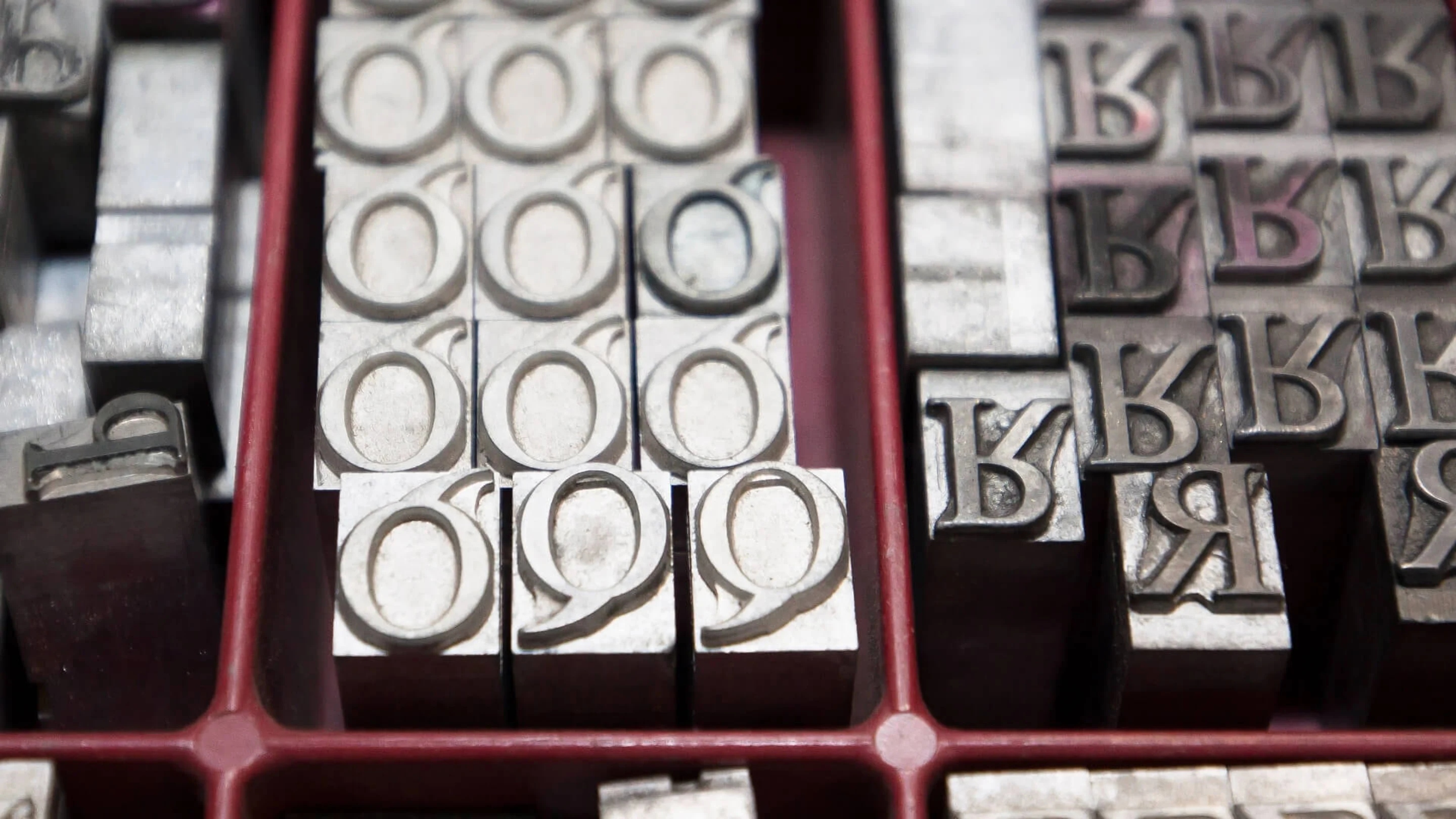
ご存知のとおり、サンセリフ書体はPCでの作業やオンライン上のテキストを表示する際に幅広く使用されています。その一方でセリフ書体は、昔から変わることなく紙媒体のデザインに適しています。
セリフ書体を認識するのは非常に簡単。それぞれの文字のストローク(一筆の動きのこと。aやeであればストロークは1つ。fやtであればストロークは2になる)の端にごく小さな線(例えば、ボール・ターミナル:文字の端に施される球状の装飾のこと、もしくはセリフ:ストロークの端にある飾りのこと)があるのがセリフ書体です。読みやすい文字という事実と離れた視点からみても、セリフ書体は、読み手に負担をかけることなくスムーズに次の文字を目で追うことができ、また認識しやすくしているのです。
昔から使用されている伝統的なタッチをあなたのデザインに取り入れられるよう、素敵なフリーのセリフ書体を厳選してみました。
まずご紹介するフォントは、Fabian De Smetがデザインを手がけた「Butler」です。 BodaniとDala Flodaのフォントからインスピレーションを得て作り出されたこのフォントは、本・ポスター・見出しや招待状でつかうとピッタリです。
Cyril Mikhailovがデザインを手がけた「Fakedes」は、丸みを帯びた2つの線から成るセリフ書体です。見出しでの使用がこの上なく似合います。
Classic Romanフォントからインスピレーションを得た「Forum」は、主にタイトルや見出しで使用するためにデザインされました。それだけではなく、パラグラフ(上記画像のような、ひとまとまりの文章のこと)での使用も素敵ですね。Denis Masharovがデザインを手がけたフォントです。
「Muchacho」は、独特な雰囲気のある全て大文字のフォントです。 Jeff Schreiberがデザインを手がけたこのフォントは、見出しで使うのにふさわしいでしょう。
Nicolás Silvaがデザインを手がけた「Poly」は、縦線を強調し、グリフ(文字の骨格作る抽象的な考えのこと)のあるウェブフォントです。
Iván Núñezがデザインを手がけた「Barbaro」は、1960年代の雰囲気を漂わせたいデザインにピッタリなヴィンテージ感のあふれるフォントです。
SuperBruutが作成した「Le Super Serif」は、88本もの合字(隣り合う文字を接続する手法のこと)と特殊な代替文字を使用した、見るからに流行を意識したフォントです。
Sean Coadyがデザインを手がけた「Firefly」は、手書きのような独特ののセリフ書体です。ヴィンテージ風な雰囲気を瞬時に見る人に伝えてくれますね。
Bodoniフォントからインスピレーションを得てデザインされた「Pelmeshka」は、ブログの見出しから子ども用の本まで幅広い用途にピッタリ。Cyril Mikhailovがデザインをした、見ていて楽しくなるようなフォントです。
Fernando DíazとTipoType Foundryによりデザインされた「Fénix」は、非常に強いインパクトのあるセリフと力強さを感じるストロークにより構成されているため、おしゃれな見た目になっています。見出しとパラグラフのどちらに用いても読みやすいこと間違いなしです。
ヴィンテージ風のフォント「Akura Popo」は、Twicolabs Designにより作り出されました。力強さのある見た目とクラシックな雰囲気を凝縮したようなセリフ書体です。
Pedro Loboがデザインを手がけた「Molesk」は、見た目のとおり、古い書体からインスピレーションを得たスラブセリフ書体(スラブセリフ:読みやすさを保ちつつ、太さを強調したセリフ書体のこと)です。素晴らしい見栄えの文字に少し注視してみましょう。それぞれの文字にレンダリングされた影がうっすらと浮かんでいますよね。このちょっとした工夫が、文字の仕上がりにより素晴らしいエッセンスを加えているのです。
「Rancho」には3つのスタイルがあり、全てのスタイルにワイルドウエスト(アメリカの西部開拓時代:1860年代~1890年頃)の雰囲気があります。さまざまな用途に使用できるこのフォントのデザインは、Nach Oh!によるものです。
この美しい「Bariol Serif」のデザインを手がけたのはAtipo。「Bariol Serif」は、スッキリとした線で構成されていて非常に読みやすいフォントのため、見出しやパラグラフでの使用がピッタリです。
Philatypeがデザインを手がけた「Lovato Light」は、幾何学的な構造をしていますが、それだけではなく、碑文の文字が持つ独特な印象を見る人に与えてくれます。
女性らしい雰囲気が微かに漂うクラシックなフォント「Yeseva One」は、The TypeTypeによるデザインです。
力強いコントラストとシャープなセリフがある「Luthier」。Adrià Gómezにより作成されたこのフォントには4つのスタイルがあるため、幅広い用途に使用できます。
Garamondの手法にインスピレーションを得た「Cormorant」は、ディスプレイフォント(見出しなど、大き目のサイズで文字を表示することに適した装飾文字のこと)です。Christian Thalmannが最適化を施したので、高解像度と大き目のフォントサイズに適用できます。
Hendrick Rolandezがデザインを手がけた「Valyrie」は、ロゴ、ブランディング、ファッション誌への使用にピッタリのおしゃれなフォントです。
ストロークのコントラストとくさび型のようなセリフを適度に加えることで、「Ledger」は非常に読みやすいフォントになっています。このフォントのデザインを手がけたのは、Denis Masharovです。
「Jura」にも21. Ledgerのように、書体にさまざまな雰囲気を加えてくれる、くさび型のセリフが施されています。Daniel Johnsonが手がけたこのエレガントなフォントには、Regular、Italic、BoldとBold-Italicの4つのスタイルがあります。
HomesteadやMuseoといったフォントからインスピレーションを得た「Palacio Font」は、上品で細い線から成る非常にシンプルなフォントです。Nathan Thomsonによるデザインです。
「Tryst」で表示された文章は、目で追いやすく非常に読みやすいですね。 Philatypeがデザインを手がけたこのセリフ書体は、パラグラフのフォントとして使用すると見る人の目をくぎ付けにできるでしょう。
Agga Swist’blnkは、アメリカの西部開拓時代を思い起こさせるような書体を頭に思い浮かべながら、このフォントをデザインしました。「Blnc」は、ロゴ、見出しやポスターをはじめとするさまざまな用途に幅広く使用できます。
幾何学的で魅力のある古さを醸し出す「Hagins」は、ブランディングやロゴへの使用がピッタリです。 Font Fabric向けにMiroslav Bekyarovがデザインを手がけたフォントです。
主にエディトリアル・デザイン(雑誌や書籍など出版物のデザイン)向けに作成された「Brela」は、少し縦長のエックスハイト(各フォントの小文字”x”の高さのこと)を取り入れているため非常に読みやすいですね。Makarska Estudioによるデザインです。
Jonathan Hillがデザインを手がけた「Modum」は、古き良き時代の魅力に、現代的で独特な美的感覚を加えたような雰囲気のフォントです。
「Kilauea」は、このコラムでご紹介するフォントの中で最もユニークなフォントの1つかもしれません。全て大文字で表示されるこのフォントは、German Di Ciccioによるデザインです。
「Kilinic Slab」は、このコラムでご紹介するフォントの中でも、より多種多様なスタイルをカバーしたフォントの1つです。Joe Princeが手がけたこのフォントは、それぞれのスタイルにおいて4種類の文字の太さとイタリック体が選択できるので、使いやすく、非常に魅力的です。
Adrian Candelaが作成した「AC Big Serif」は、上品で華奢な線とその端にある大きなセリフがうまく融合されています。ため息が出るほどの美しいフォントに仕上がっています。
Simon Walkerがデザインを手がけ、丸みを帯びたセリフと文字を横に拡張したような「MatchBook」は、素敵な見出しの作成にピッタリなフォントです。 力強さを表現し、また陰影を施すことで、古き良きアメリカ西部の雰囲気を醸し出しています。
Dan Gneidingによる「Dude」を見ていると、カウボーイの姿が頭に浮かんできませんか?力強い12種類のセリフから好きなスタイルを選べるので、あなたのお気に入りがきっと見つかるでしょう。
1800年代のお芝居のビラや広告からインスピレーションを得た、このヒューマニスト・フォント(サンセリフ体の分類の一つ)には、がっしりとした力強いセリフが施されています。「Abraham Lincoln」は、Frances MacLeodによるデザインです。
フォントのデザインを手がけたAlonzo Felixは、老舗のサーカス団の広告バナーから、「Tight Rope」のインスピレーションを得ています。 微かな曲線と強調したセリフがあるので、ヴィンテージ風のポスターにピッタリなフォントです。
Andrew McCluskeyがデザインを手がけた「Serrific」は、きれいでシンプル、かつクラシックな雰囲気が漂うフォントです。 見栄えも良いので、間違いなく素晴らしいクオリティのフォントです。
Lukas BischoffとSascha Timplanがデザインを手がけた「Athletico」は、現代的でおしゃれ、かつ必要最低限の装飾が施されたフォントです。
うまく説明ができないのですが、Grzegorz Lukが手がけた「Foglighten」を見ると、著者はシャネルのNo.5(シャネルの香水のブランド名のこと)を思い出します。はっきりとその理由が分からないのですが、おそらく魅力的な合字がそうさせるのでしょう。 このフォントを見出しで使用すると、素晴らしく引き立つでしょう。
水平でフラットなセリフ、短いディセンダー(エックスハイトより下にある部分のこと)、ゆったりとした曲線に、直線的なイタリック体。Julia Zhdanovaが手がけた「Artifica」は、筆者が気に入っているセリフ書体の1つです。
Ben Dalrympleが手がけた「Geared」は、産業的文化からインスピレーションを得たフォントです。文字の太さが4種類あるので、TPOによって使い分けることができますね。
GLUK fontsがデザインを手がけた「Kawoszeh」は、洗練された文字のストロークがある非常に伝統的なフォントです。
Lucas AlmeidaとDmitry Goloubが作り出した「Bobber」は、とても楽しげなムードとヴィンテージ風の見た目をした、全て大文字のスラブセリフ書体です。書体の主軸から少し外れたデザインが特徴です。
Wesley Jefferiesが生み出した「Superlative」は、年鑑、ダイナー(軽食のレストラン)やアールデコ調からインスピレーションを得た、全て大文字のフォントです。
本のデザインや編集プロジェクト向けにデザインされた「Unna」は、繊細なセリフと力強さがある文字の縦線から成る、オープンソース(ソースコードが一般公開されていること)のフォントです。「Unna」は、Jorge de Buen UnnaとOmnibusTypeによるデザインです。
René Biederがデザインを手がけた「Choplin」は、シンプルさ・幾何学的・中立性の3つのメイン要素から作り出されています。このフォントのOpen Type(マイクロソフト社とアドビシステムが共同開発をしたデジタルフォントの規格のこと)の特徴により、幅広い用途に使用できます。